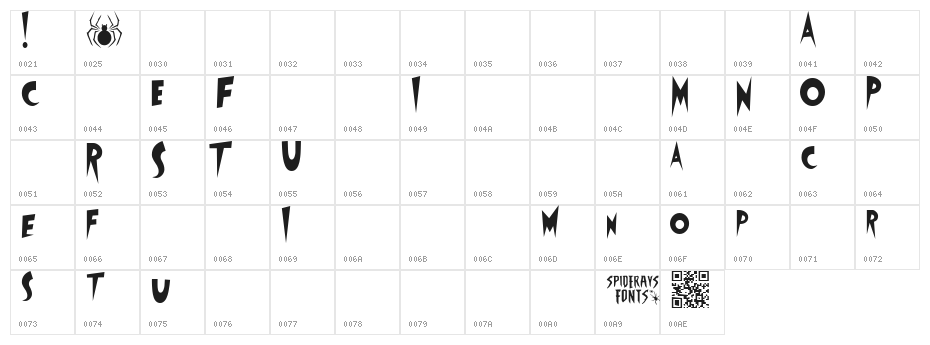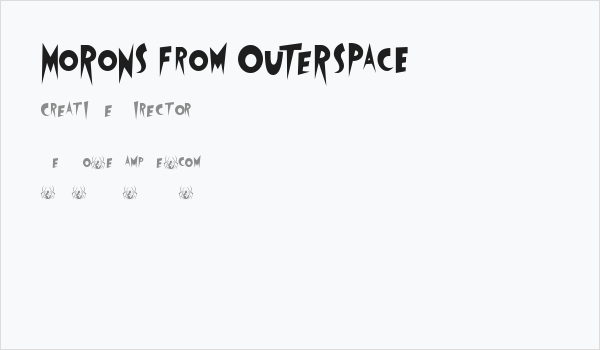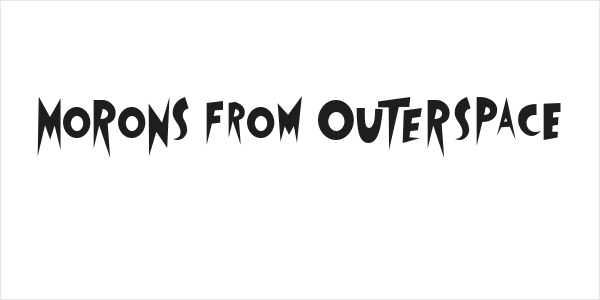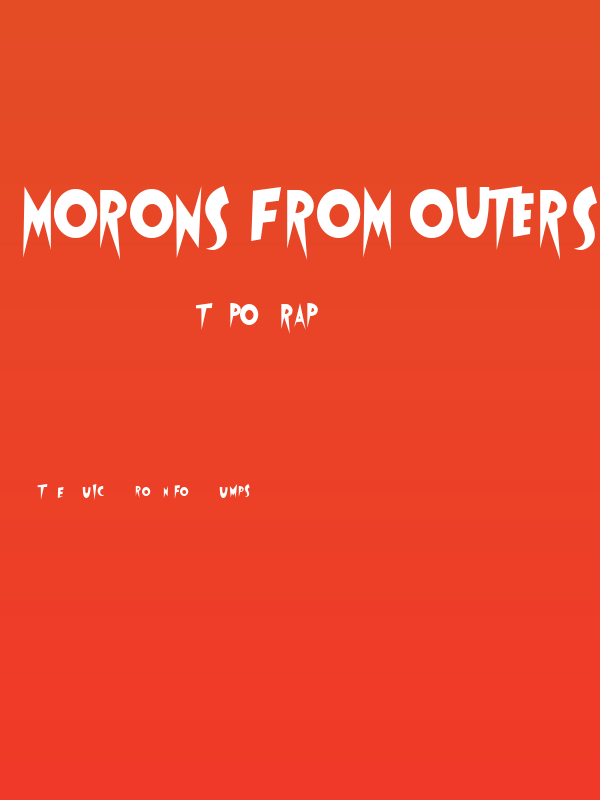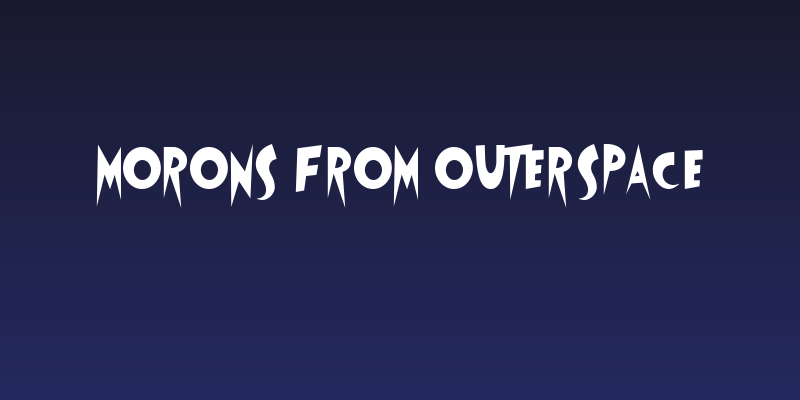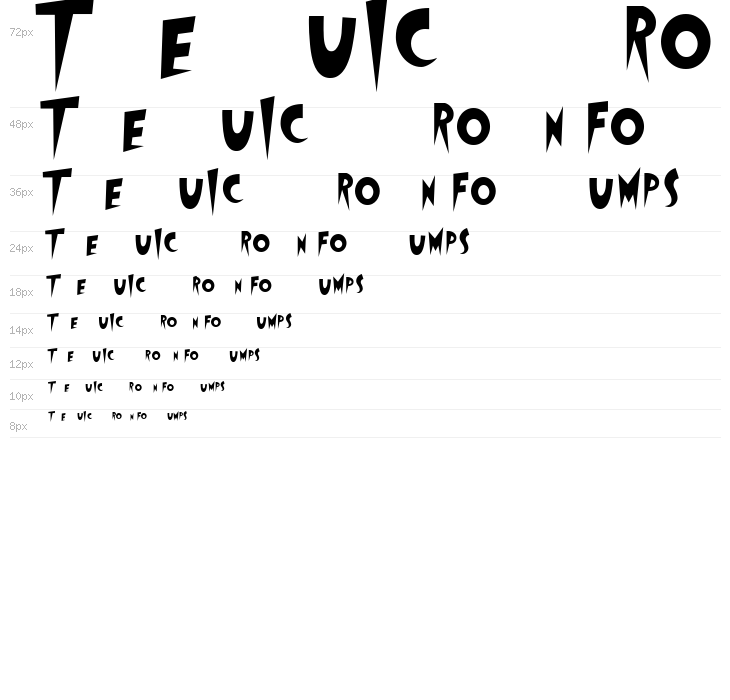
MoRoNs from OuTeRsPacE Font
MoRoNs from OuTeRsPacE
| Progetti proposti | Perfect for Halloween-themed posters, party invitations, children's book covers, or any project requiring a fun and spooky vibe. |